「スピード」で選ばれる書体
朝日新聞東京本社 メディアビジネス局 業務推進部
アートディレクター 末松 学史氏
株式会社 テキストハウス
チーフグラフィックデザイナー 宮本 一歩氏
朝日新聞社メディアビジネス局は、コンテンツや取材力を活かしながら広告特集を制作し、トーン&マナーを管轄しています。1 ヶ月に60 件以上となる広告特集は、テキストハウス社を始めとしたブレーンとなる制作会社とともに、クライアントの要望を聞いてから平均3~4 週間で制作され、常に10 本以上のプロジェクトが同時進行しています。
「新聞広告の制作は、ほとんどを瞬時に決めていかなければなりません。それは制作本数の多さや期間の短さが理由ですが、『瞬時に決めること』が新聞づくりに合っているのです。読者は新聞を開くと同時に、興味があるかどうかを判断します。作り手も、時間をかけてこなれたものにしてしまうのではなく、瞬時に判断することで読者との感覚が合っていくと思っています」と、メディアビジネス局 アートディレクターの末松氏は語ります。
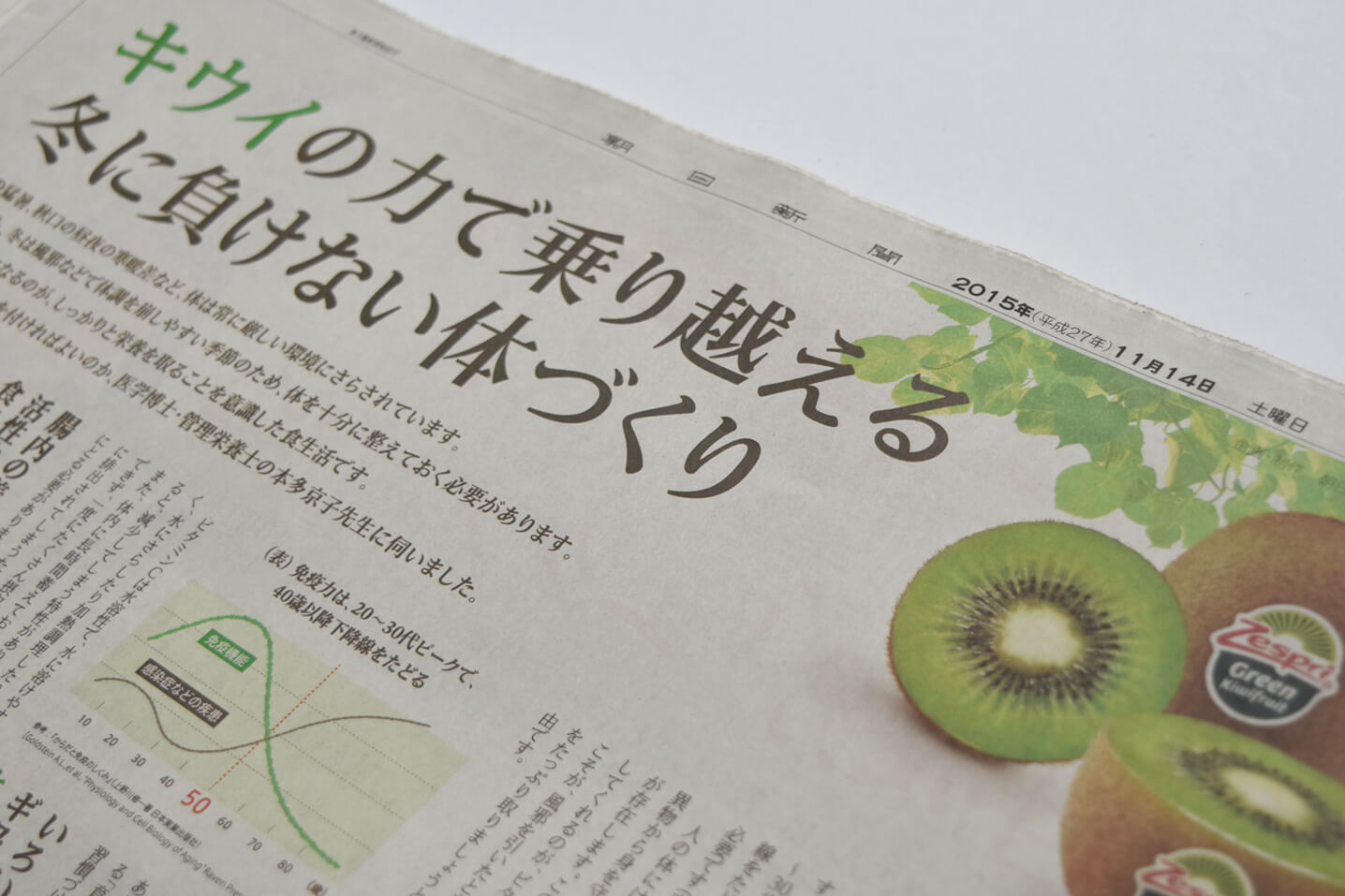
新聞広告制作では、初稿の段階でフォントやレイアウトの変更、カラーやトーンの修正などのすべてを決定するため、パソコンでの作業は数日でおこなわなければなりません。
「TP 明朝は他のフォントに比べて微調整が少ないという印象です。そのままで違和感がありません。小ぶりにつくられている仮名を大きくする、感嘆符の前後に半角スペースを入れるなどの指示で時間をとることがありません。分刻みでの入稿ですので、制作時間を削減して効率よく作業ができるので助かっています」(末松氏)
朝日新聞の本文は朝日新聞明朝と呼ばれているオリジナルの書体が使われていますが、広告ではいろいろなフォントが使用されています。ゼスプリ社の広告では、従来のフォントにはない新しさと、キウイの親しみやすさやフレッシュさを表現し、商品とよく馴染みながら読みやすいフォントを探していました。
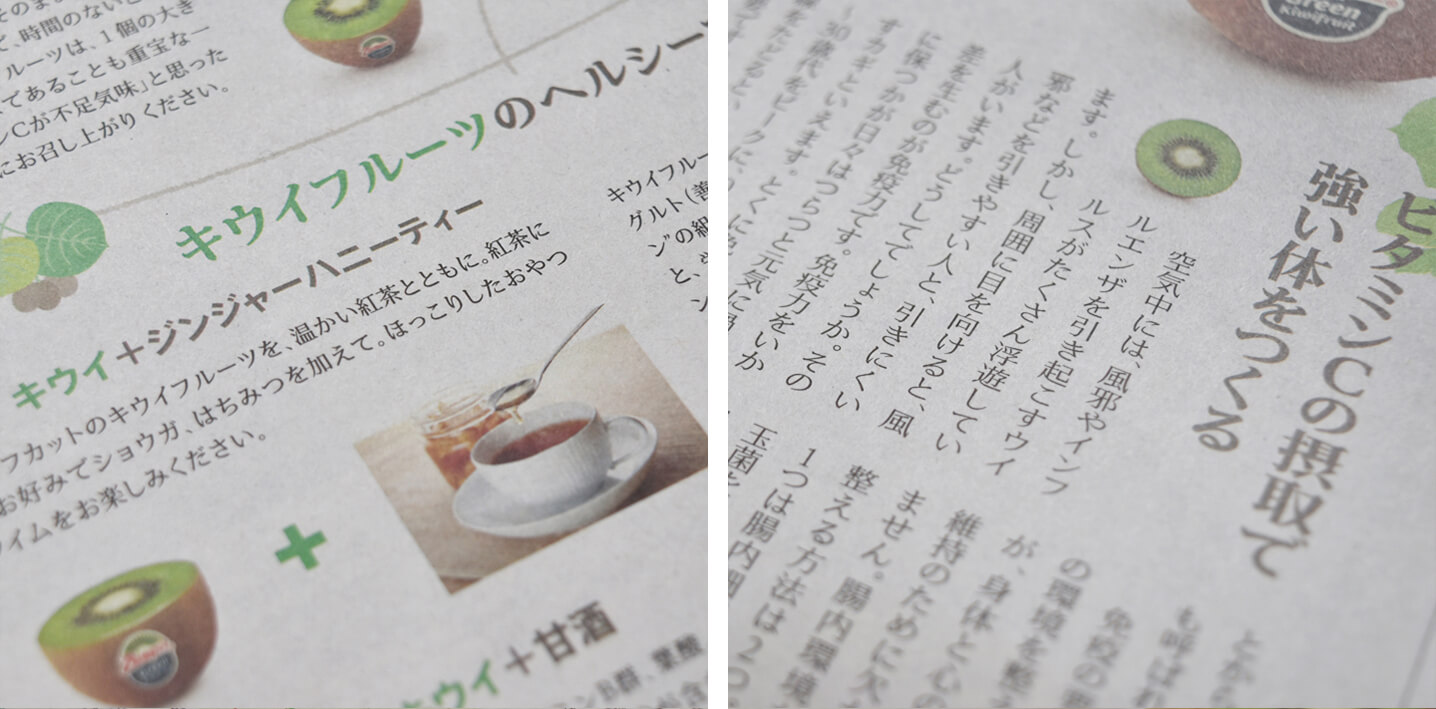
テキストハウス チーフグラフィックデザイナーの宮本氏は「現代的で、ウロコが気にならない明朝体を探していました。それまで使っていた書体が時代に合っていない気がしてきたのです。一番よく使っているAXIS Font に合う明朝体を探していたのですが、選んだのはやはりTP 明朝でした」と語ります。宮本氏はTP 明朝に女性的な印象を持ったと言います。ゼスプリのセミナーでは講演者にも女性がいること、広告のターゲットが女性であることも採用の理由のひとつ です。
「TP 明朝は完成度が高くて現代的です。フォントの完成度の高さは、広告商品の完成度をより高くみせる効果があると思っています」(宮本氏)
朝日新聞社メディアビジネス局が制作する広告特集では、AXIS Font も多く使われています。従来は、ゴシックフォントのアウトラインを加工して新しい表現をする手法を使っていましたが、加工せずに使えるフォントとしてAXIS Fontを選択しました。明治メイバランスの広告では、購買者が興味をもつ情報を増やすとともに、読者に響くフォントとしてAXIS Font を選択し、前回の広告を上回る反響となりました。
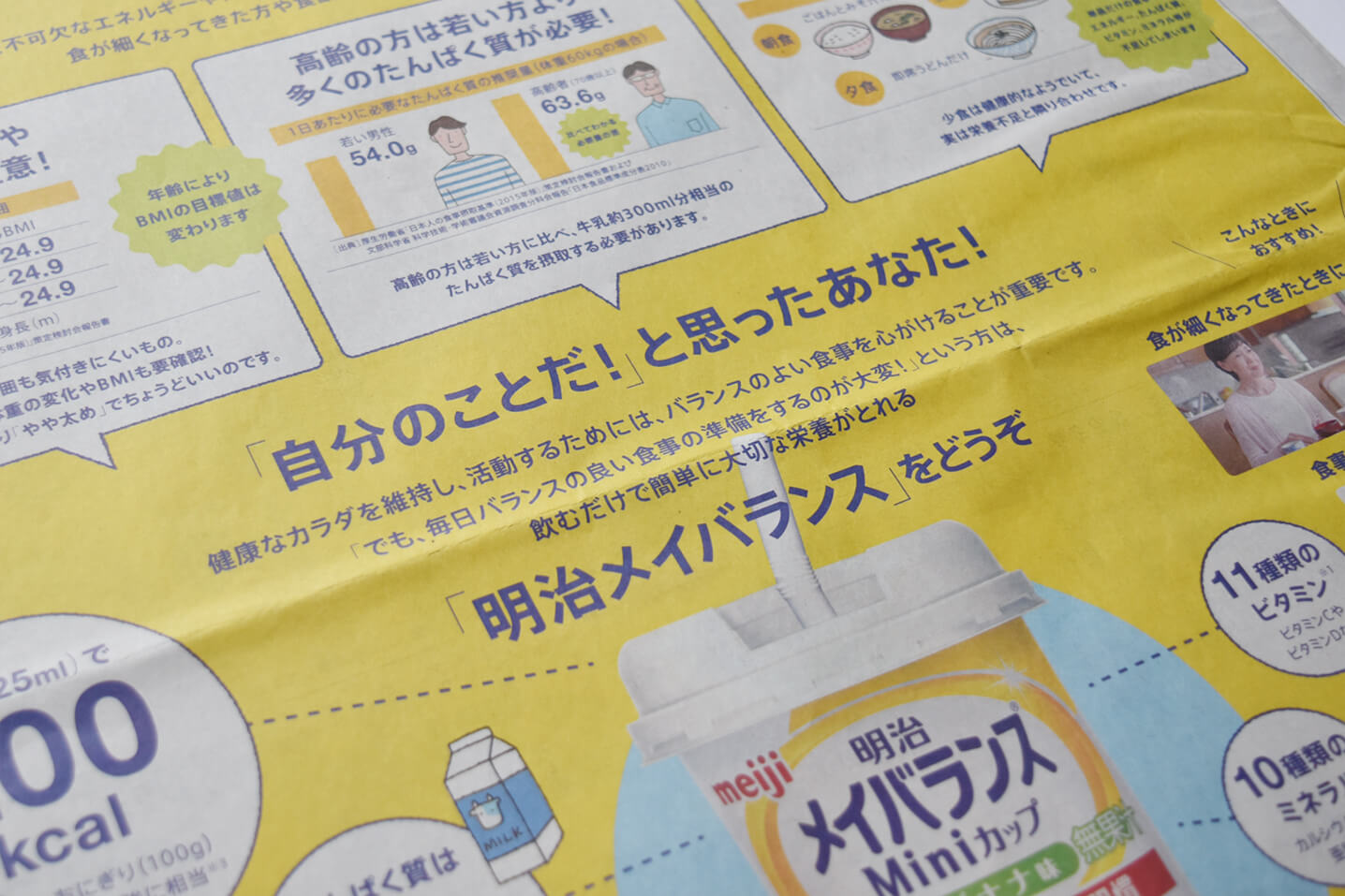
「AXIS Font は現代的で、ふところが自然ですっきりして使いやすい。10 年ほど前から一番よく使っているフォントです。やはりAXIS Font とTP 明朝の組合せはぴったり合うので、意識していたわけではないですが、この組合せになることが多いですね」(宮本氏)
末松氏は、AXIS Font の導入によりデザインの幅が広がったと感じたそうです。「広告を作っていると、ひと文字の主張が気になることがあります。隣の文字まで侵食してお互いに攻め合っているようなイメージです。AXIS Font は、たとえば『ひ』などの長い部分が控えめだったり、『の』の周りが空きすぎないなど、研究されているなと感じます。ずっと気になっていた文字の細かい部分を解決してくれたAXIS Font は、『文字の特効薬』です」
最初にTP 明朝を見た時は、あまり見たことはないけどすんなり入ってくるという印象でした。今ではすっかり馴染んでいるので、ずいぶん前からあるような気がしています。
ゴシックだと少し軽く感じ、明朝体だと真面目過ぎて商材に合わない。今までとは違う、それでいて読みやすいフォントをずっと探していていました。TP 明朝は、縦書きでも微調整がほぼ必要ないので助かっています。